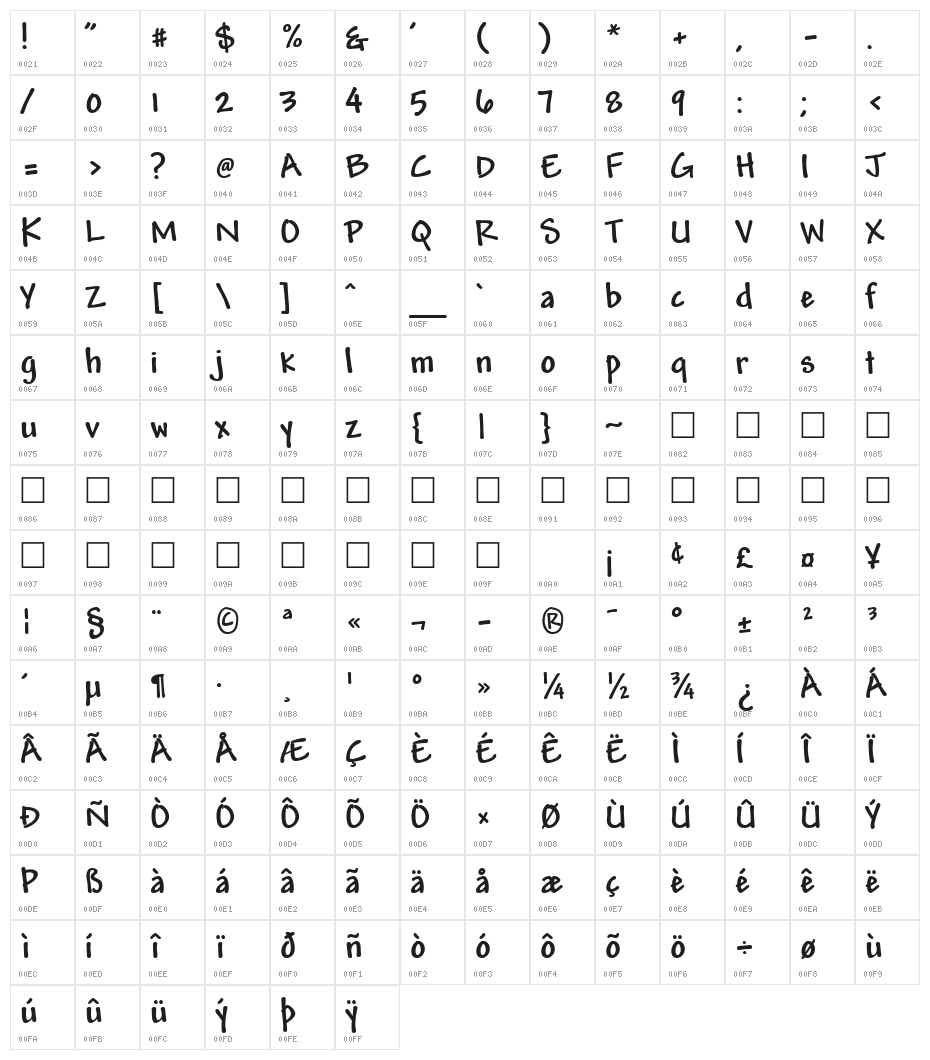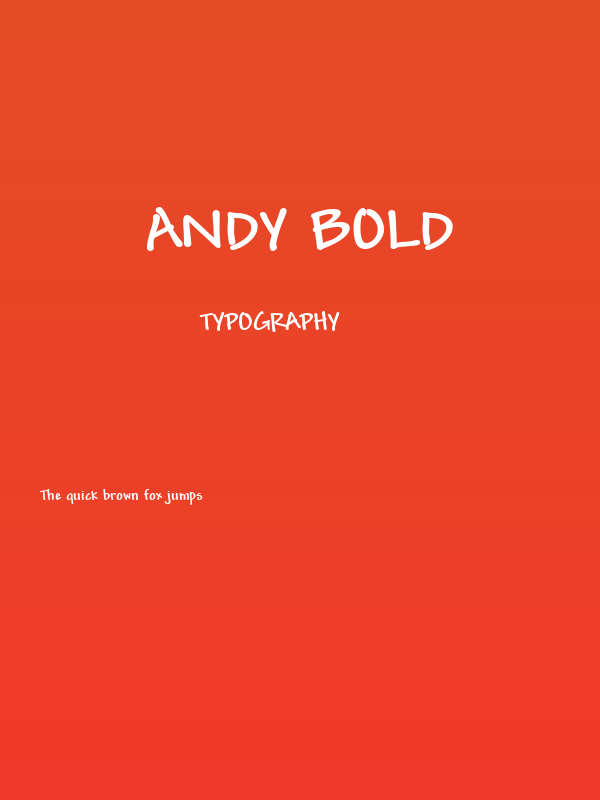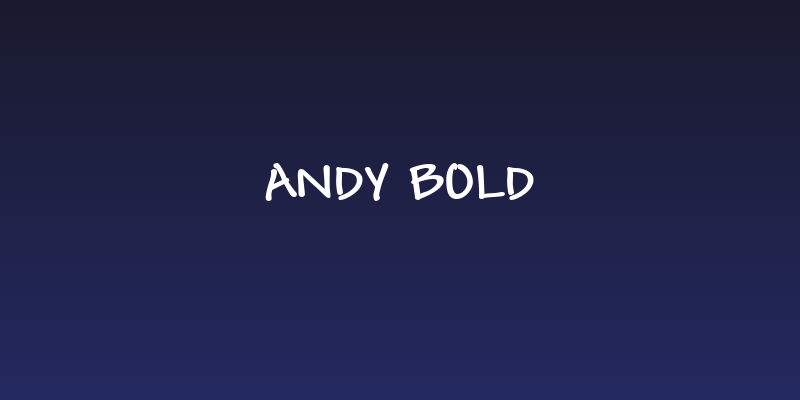
Andy Bold Font
✎ Handwritten
| श्रेणियाँ | Handwritten |
| समग्र शैली | Casual |
| उपयोग का मामला | Headlines, Logos, Informal Text |
| सुझाए गए प्रोजेक्ट | Ideal for greeting cards, children's books, casual branding, and social media graphics. |